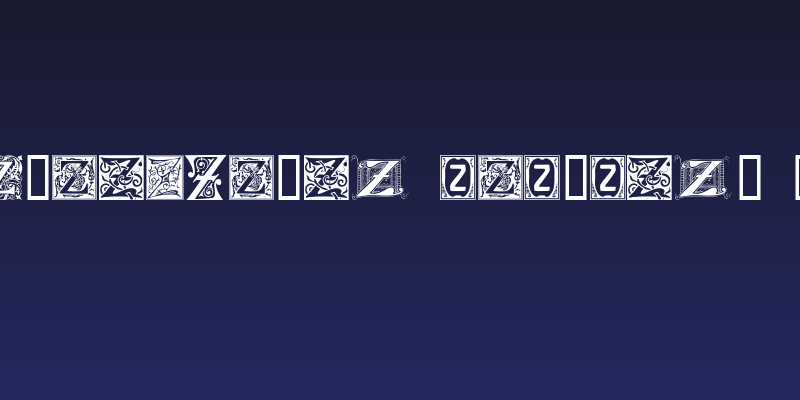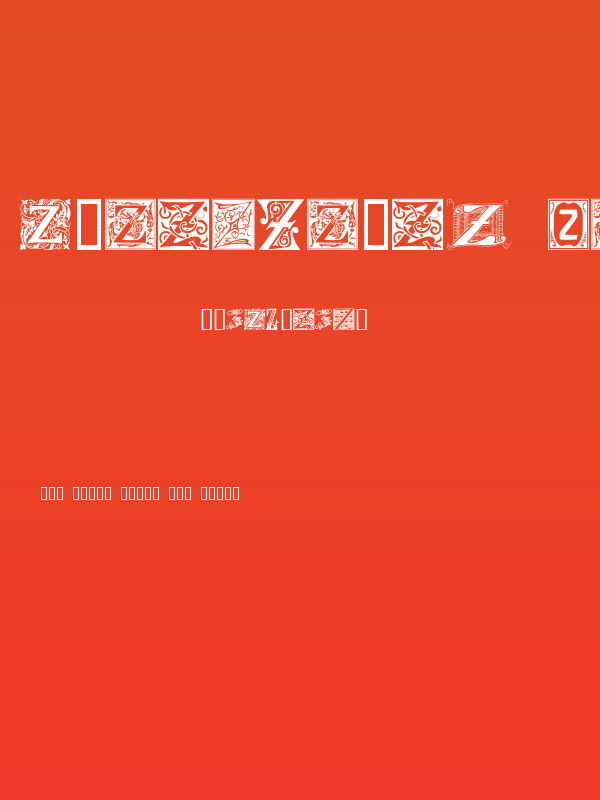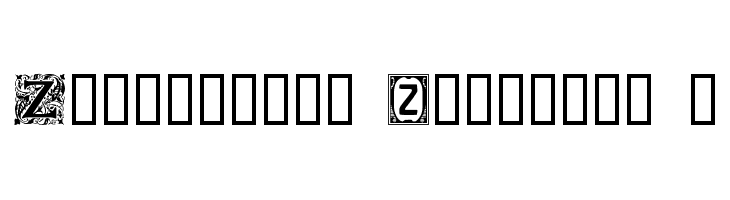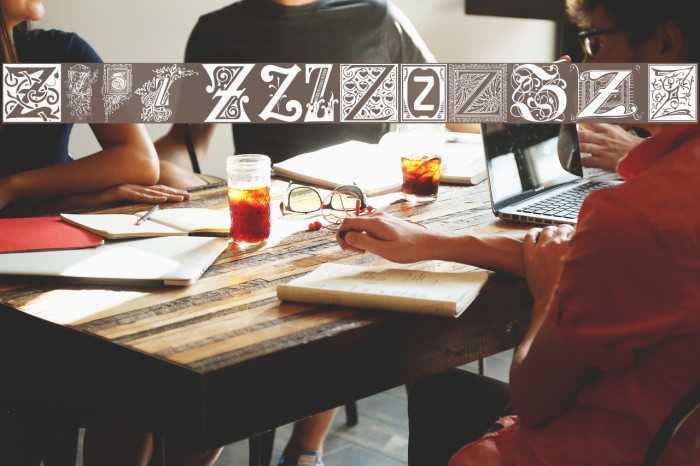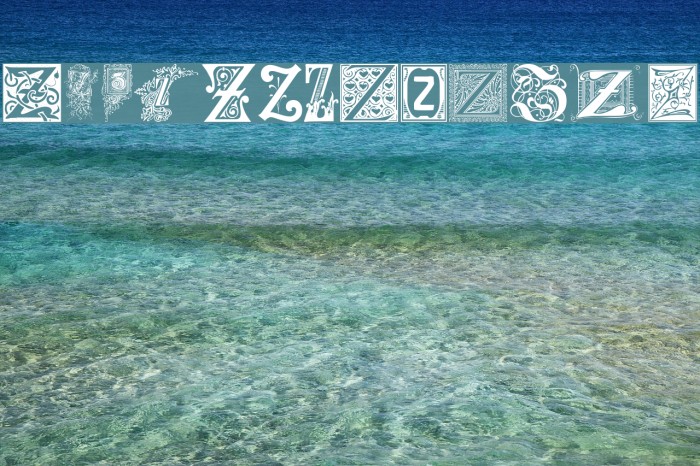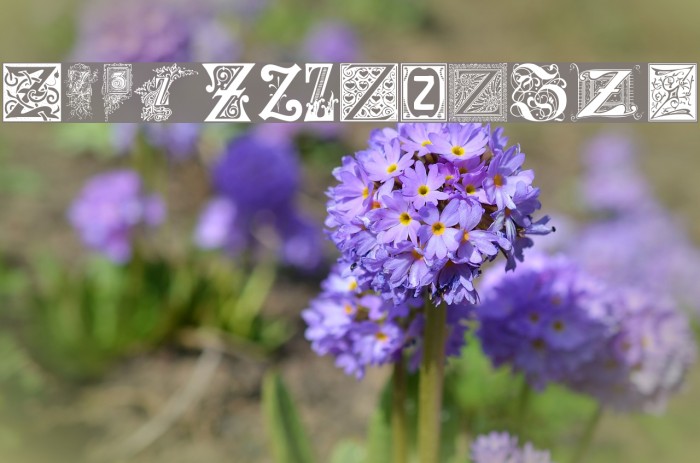
Ornamental Initials Z Font
✎ Retro
| Categorie | Retro |
| Caso d'uso | Logos, Headlines, Decorative text |
| Progetti proposti | Ideal for use in wedding invitations, luxury branding, vintage book covers, and decorative certificates. |